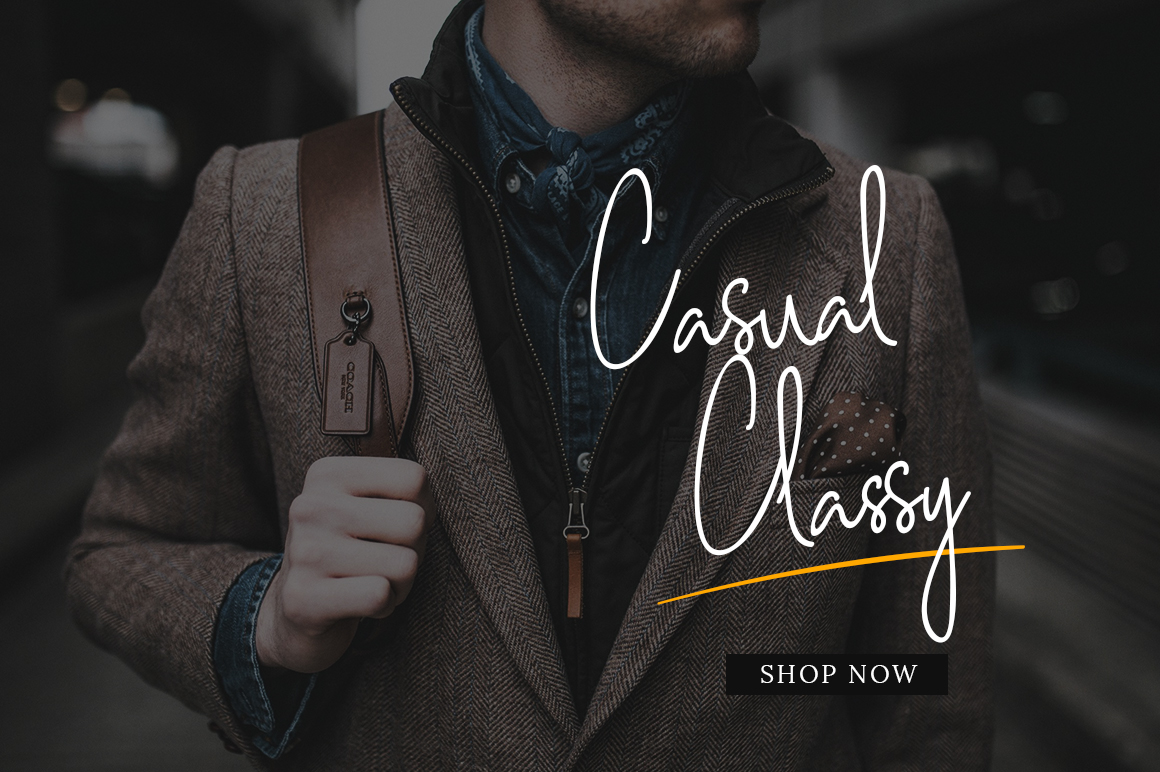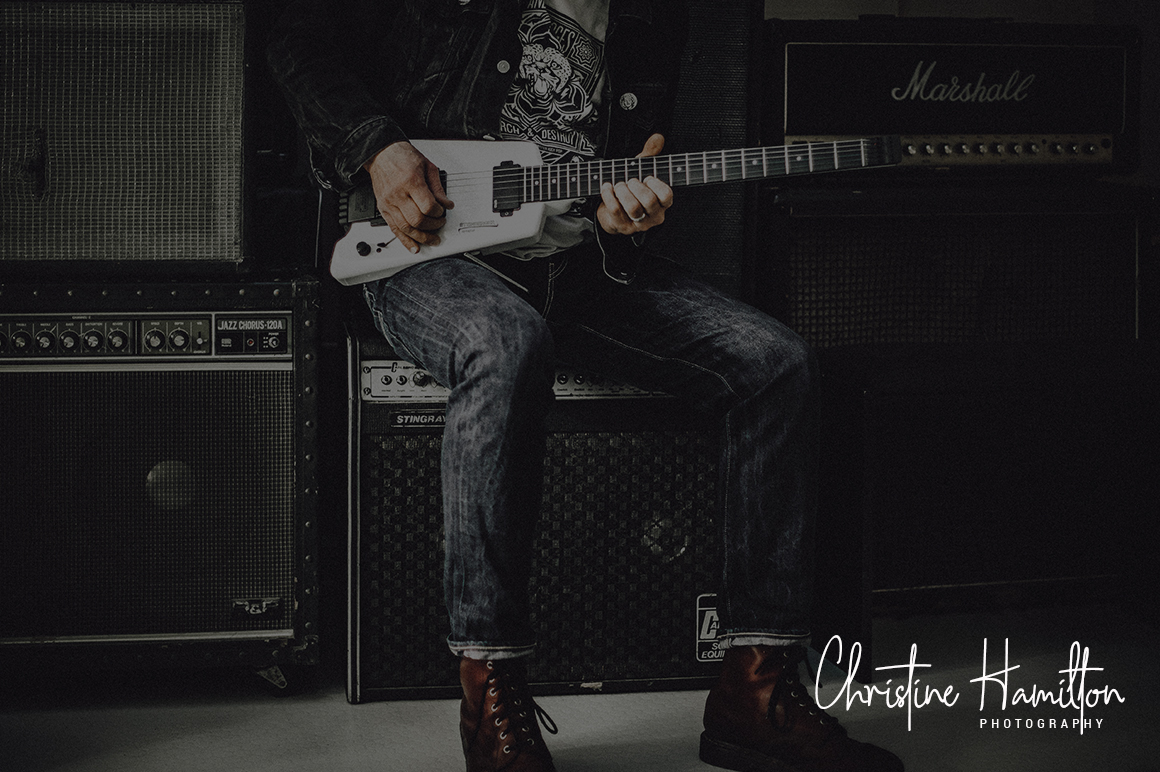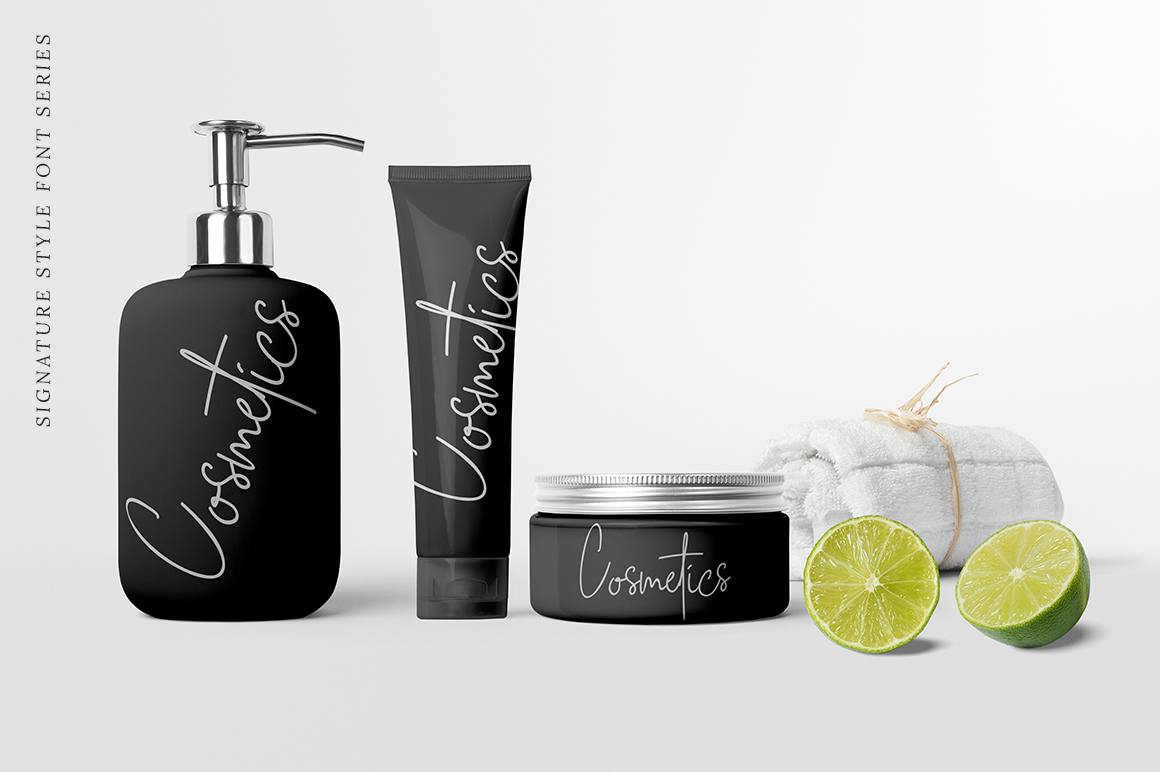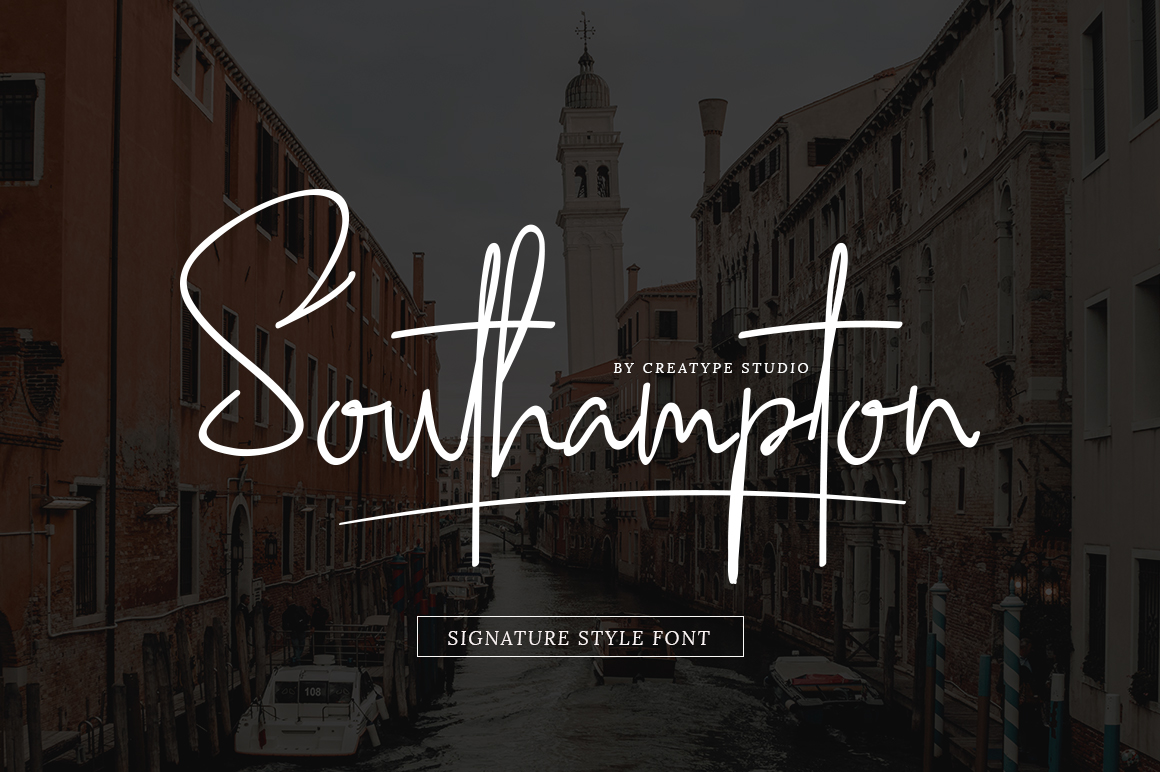
FONT DEL GIORNO : SOUTHAMPTON SIGNATURE
Il font che vi presentiamo oggi é: SOUTHAMPTON SIGNATURE
SOUTHAMPTON è il nuovo font realizzato da Creatype Studio Co.
Southampton di Creative Studio è uno splendido esempio di font tipografico fatta a mano, perfetto per qualsiasi progetto di design come loghi e branding, inviti di cerimonia, post sui social, pubblicità, packaging, design di prodotti, etichette, fotografie, filigrana o wathermark, eventi speciali o tutto ciò che ha bisogno di quel gusto autentico della scrittura a mano.